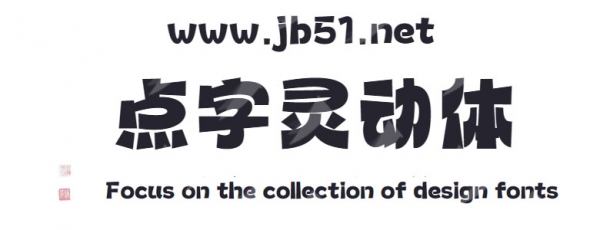
點(diǎn)字靈動(dòng)體是由點(diǎn)字庫(kù)推出的藝術(shù)字體,字體筆畫(huà)融合幾何圖形設(shè)計(jì)感,傾斜的姿態(tài)與粗壯的筆畫(huà),相映成趣,形成一種塊面感強(qiáng),適合應(yīng)用于藝術(shù)設(shè)計(jì)、各類廣告和產(chǎn)品包裝設(shè)計(jì)等領(lǐng)域。
筆畫(huà)融合幾何圖形設(shè)計(jì)感,傾斜的姿態(tài)與粗壯的筆畫(huà),相映成趣,形成一種塊面感強(qiáng)、撇捺的弧度設(shè)計(jì),視覺(jué)上醒目、給人以沖擊力。適用于廣告標(biāo)題、產(chǎn)品包裝、影視海報(bào)等應(yīng)用場(chǎng)合,此外,字體呈現(xiàn)出的日式感,用在與日本文化相關(guān)的場(chǎng)景也很適合。